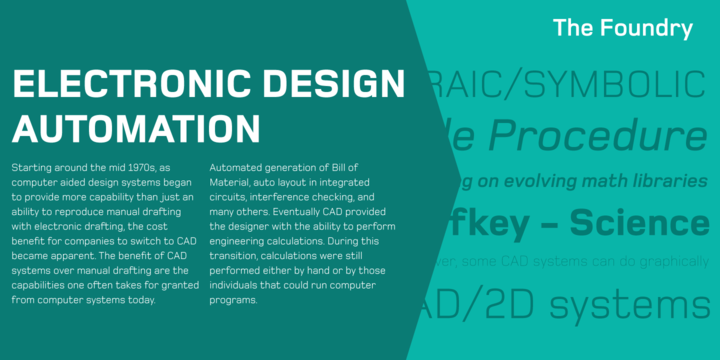
Alternative Schrift gesucht
Hallo Zusammen,  ich bin gerade auf der Suche nach einer Schriftalternative für die Eurostile (das ist doch die Eurostile - siehe PDF - oder etwa nicht). Im Prinzip suche ich einen ähnlichen Font, der aber ein bisschen moderner wirken soll. Hat vielleicht jemand eine Empfehlung?
Yep, das ist die Eurostile. Alternativen haben wir hier schon mal zusammengetragen:
...und wo ich schon mal dabei bin bräuchte ich noch einen kreativen Rat.
Ich suche gerade zu einer passenden Fließtextschrift für angehängtes Logo.
Aktuell habe ich jetzt mal die News Gothic genommen.
Oh, die Tofino ist ein toller Tipp!
Ich habe mal eine Verständnisfrage an die Kollegen Schriftgestalter. Bei der Tofino steht:
Eight weights of “West Coast Swiss,” designed for the screen.
Wenn eine Schrift für Printzwecke gestaltet wurde, dann funktioniert sie nicht unbedingt für Screen, das kann ich nachvollziehen. Aber wie ist es umgekehrt – eine für Screen gestaltet Schrift im Printbereich zu verwenden: Ist das unproblematisch oder kann es da medienbedingte Stolperfallen geben?
Bin zwar kein Schriftgestalter, aber ich verstehe das so, dass die Bildschirmtauglichkeit ausdrücklich herausgehoben wird. Im Printbereich haben wir ja viele Anpassungsmöglichkeiten, da sind wir dann selber für ein gutes Ergebnis verantwortlich :-)